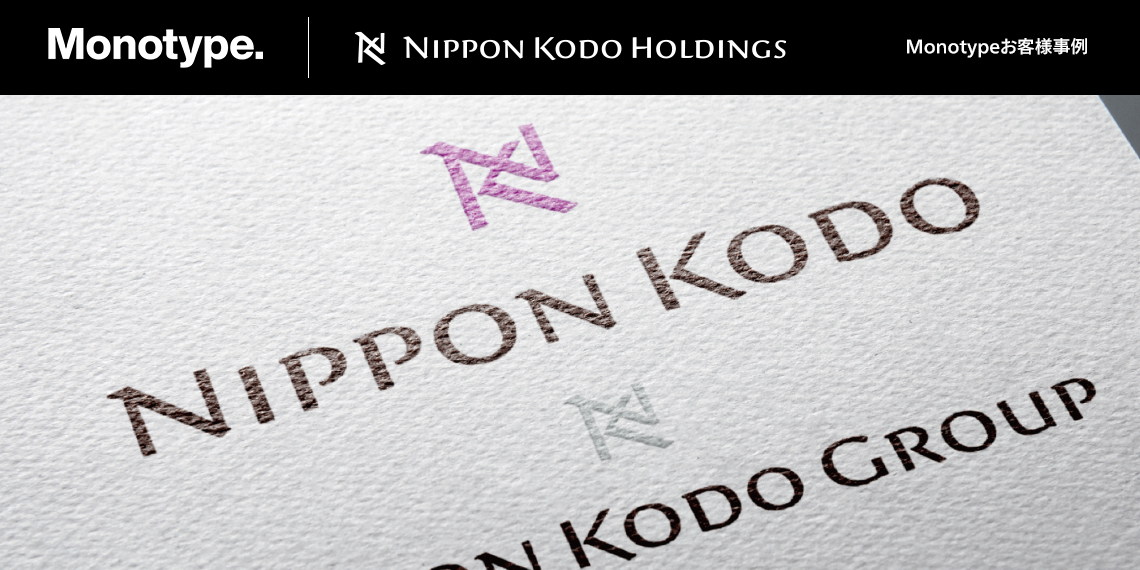
香りと時間の豊かさを表現し、歴史を感じつつも時代を超えて愛されるロゴマークを制作
450年の歴史と未来をつなぐ、日本香堂グループのロゴデザイン
1575 年から続く香の名跡「香十」を受け継ぎ、お線香やお香、そしてフレグランスブランドを、国内のみならず世界へと展開している日本香堂グループ。2025 年には450 年の節目を迎えるにあたり、「450プロジェクト “聞く~awake your spirit~”」として、新事業や新製品を含む多彩な取り組みを発表しました。
その嚆矢となったのが、新たに定められたグループアイデンティティです。グループおよびコーポレートのロゴタイプは、サン・アドのアートディレクター葛西薫氏と、Monotype® のクリエイティブ・タイプディレクター 小林章の協働によって制作されました。
450年という長い歴史を受け継ぎながら、これからの100年を見据えた日本香堂グループ。その新たなアイデンティティには、歴史を感じさせながらも、時代を超えてグローバルに愛される普遍性が求められました。新たに策定されたグループ理念「香りと旅する 日本香堂グループ」を象徴する存在として、ロゴタイプの制作が始まります。
葛西氏と小林は役割を明確に分けるのではなく、双方がアイデアを出し、それに互いが応えながらデザインを発展させていく方法で制作を進めました。さまざまな方向性を検討した末に選ばれたのは、6世紀前後の写本などに見られる「ハーフアンシャル体」をもとにしたアイデア。歴史ある文字の佇まいを現代的に整えることで、クラシックさとモダンさを併せ持つデザインを目指しました。
さらに、イニシャルのNとKを組み合わせたマークは、さまざまな香りを収める「香箱」から着想。細部まで調整を重ねながら、長く使い続けられる普遍的な美しさを追求しています。